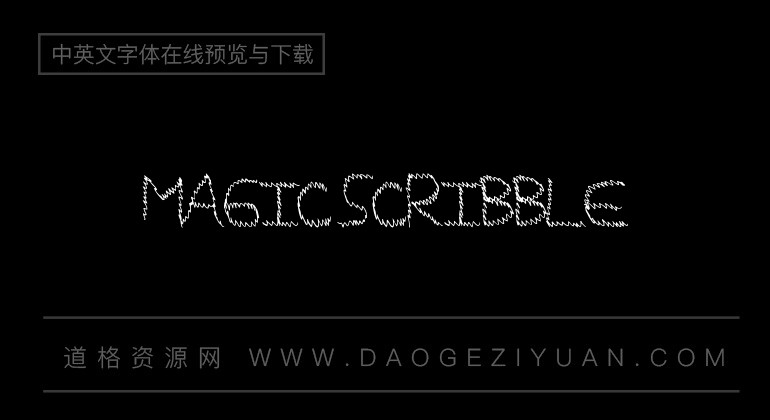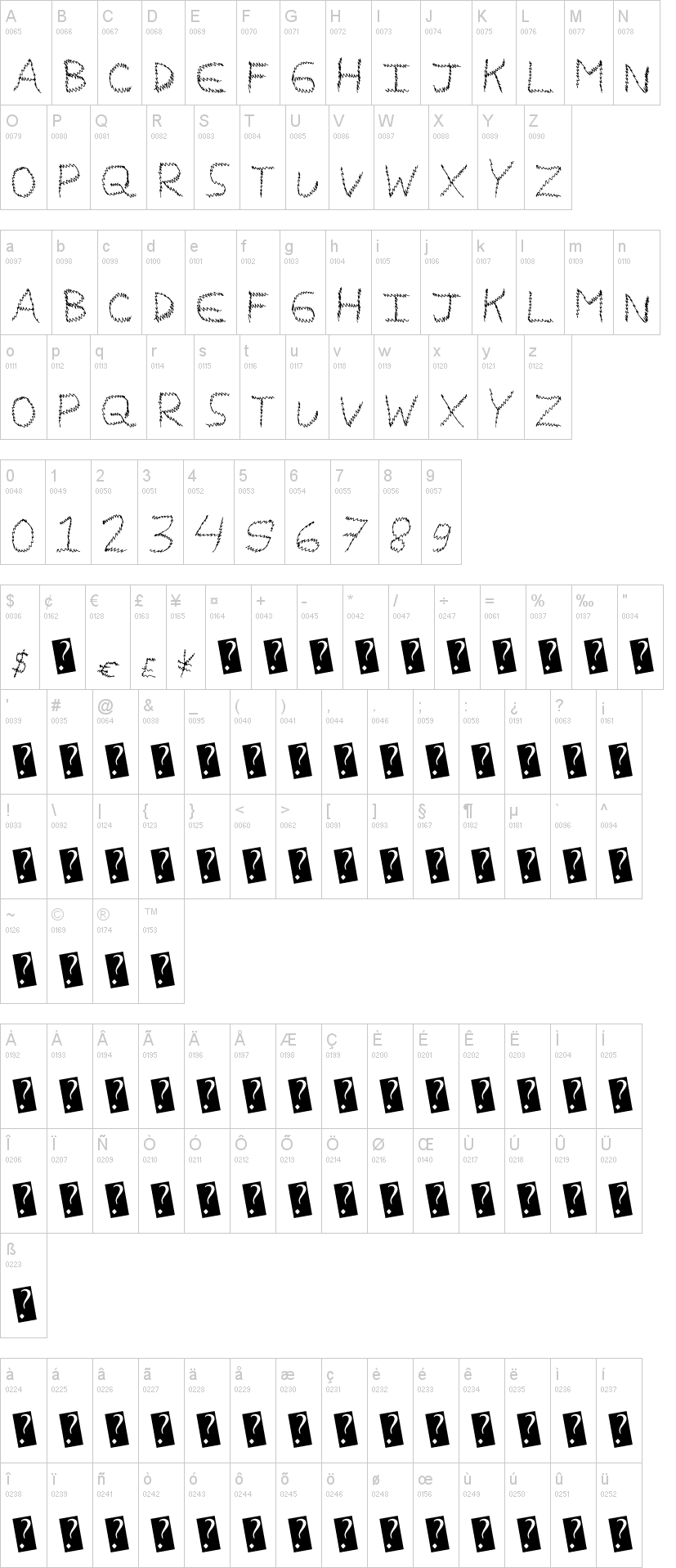
Magic Scribble 是一款新颖的字体,它具有古朴的外观,拥有活泼的笔触,可以创造出流畅而有趣的文字效果。它可以将文字变成一种艺术形式,能够让文字更具有个性,更有趣,更有趣味。Magic Scribble 字体适用于各种平台,可以在网页、印刷品、广告物料等多种场景中使用。内容介绍
Magic Scribble是一款非常不错的手写艺术字体,具有很好的视觉感,适合于文化类的宣传设计、商业类品牌的广告和产品包装设计以及个性化文字排版等较多场景。